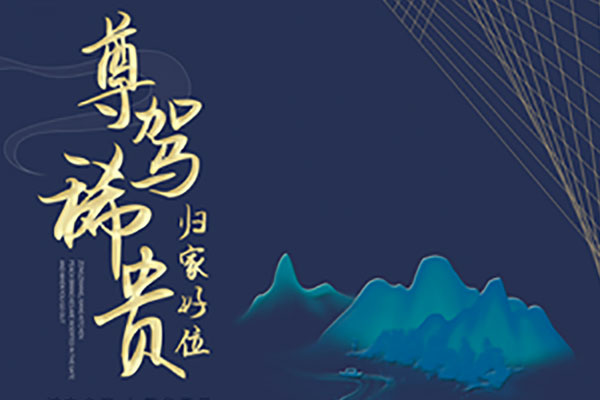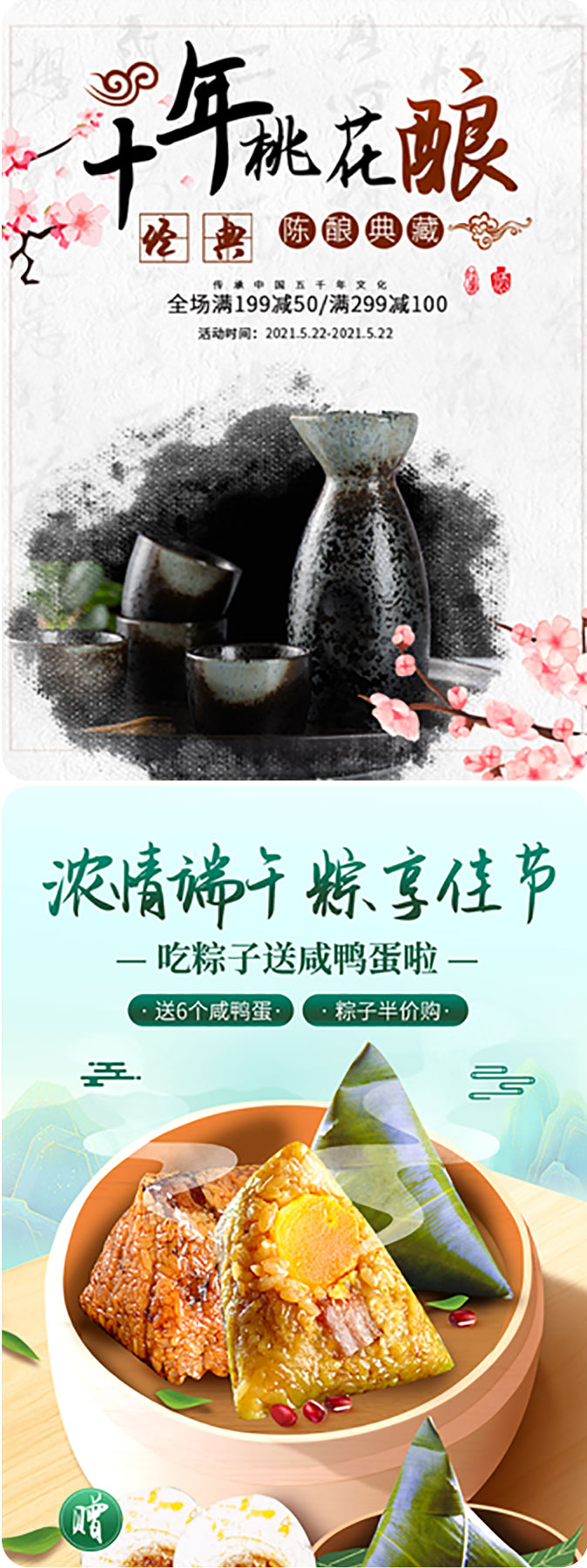
千图笔锋手写体
千图笔锋手写体:清新文艺,创新无限
千图笔锋手写体是一款由千图网精心打造的创意手写字体,以其独特的风格和清新的气息脱颖而出。这款字体在设计上融入了柔和的弧线元素,打破了传统字体的平直笔画,呈现出一种流畅而柔美的视觉效果,令人耳目一新。
千图笔锋手写体的字形简洁而有力,每一个字都经过精心设计,充满了想象力和创意。这款字体的连笔写法使得整体更加流畅,同时也为设计师提供了更多的排版和设计空间。
无论是在海报设计、影视综艺的标题制作,还是文艺宣传等场景,千图笔锋手写体都能表现出色,吸引人们的目光。它不仅符合现代审美趋势,更能为你的作品增添一抹清新和文艺的气息。
千图笔锋手写体效果预览
千图笔锋手写体字体效果预览